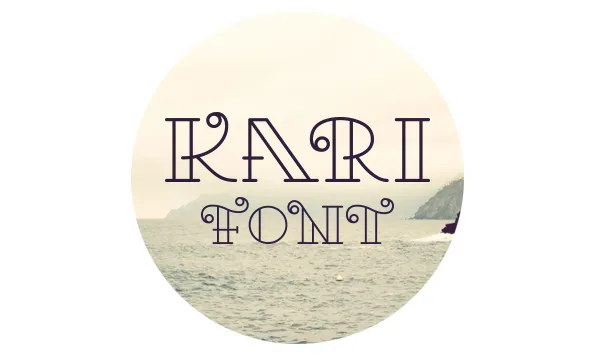
A Kari Font é uma elegante e sofisticada escolha para designers que buscam uma fonte de exibição com ares modernos e icônicos. Inspirada no trabalho do designer Hamilton, essa fonte combina elementos clean e minimalistas com um toque vibrante e alegre, perfeita para criar designs onde deseja-se destacar na tela. Seu uso permite que você apresente textos de forma única e memorável em anúncios, logomarcas, materiais publicitários ou qualquer outra aplicação onde uma fonte de exibição é desejada. Kari traz com ela uma personalidade vivida, adequada para um público ampliado que busca algo mais do que simplesmente uma ferramenta funcional: querem algo que ressoe, chame a atenção e seja o centro das atenções em qualquer meio digital.